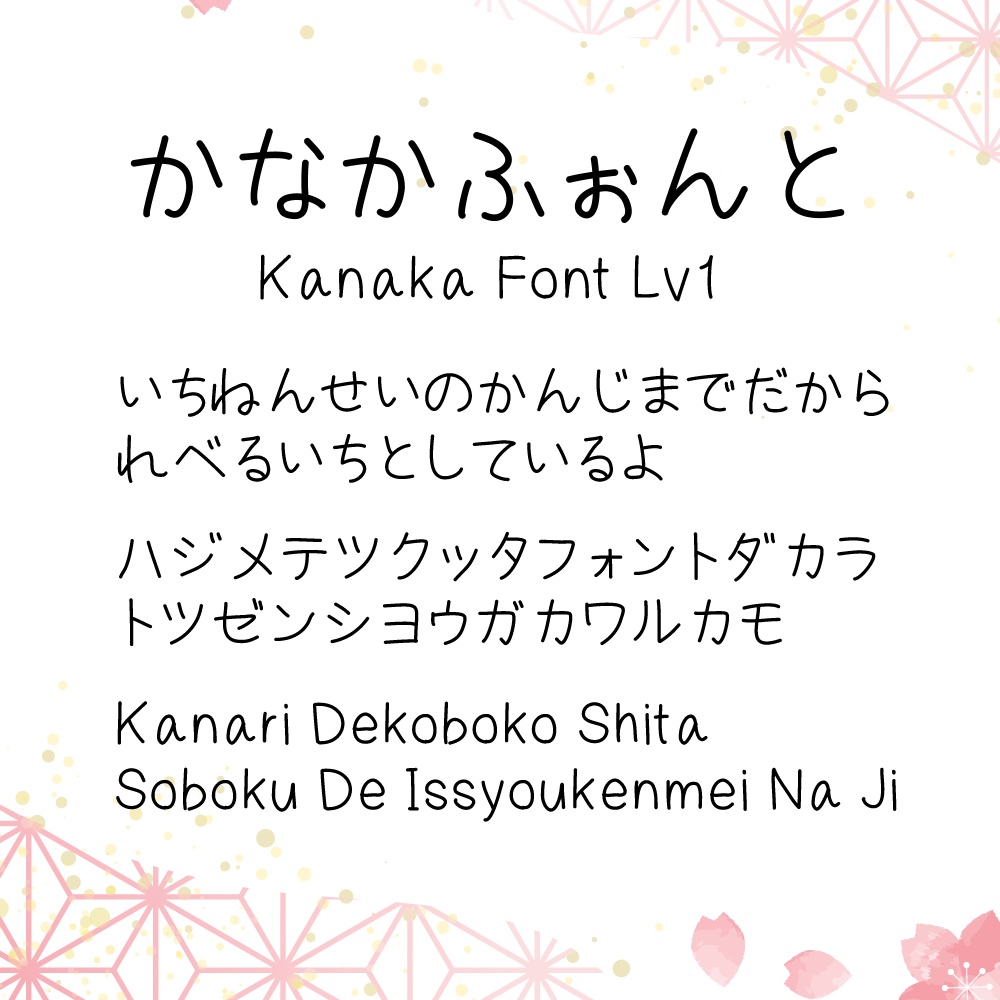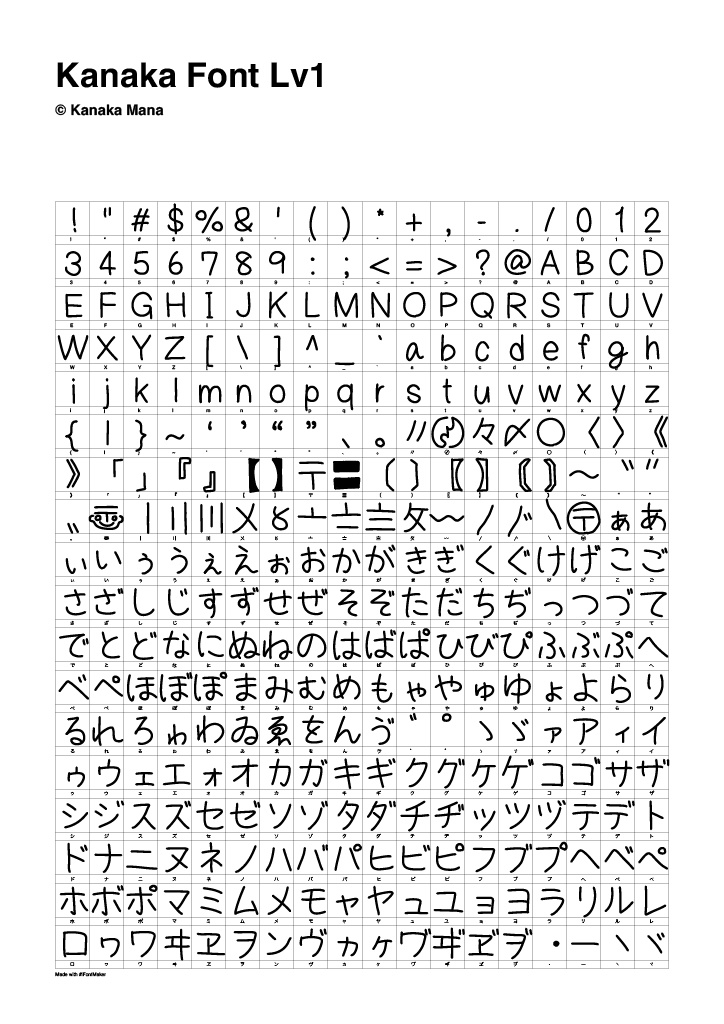
初めて作ったフォントです。 ていねいに書こうとしつつ、ちょっとでこぼこな一生懸命な手書き文字です。 TrueTypeフォント(.ttf)です。 iPadアプリ「iFontMaker」を使用しています。 無料版と支援版がありますが、内容は一緒です。
収録文字
・アルファベット ・数字 ・ひらがな ・カタカナ ・漢字 87文字(小学一年生+自分で選んだ漢字) ・記号 ちょっと